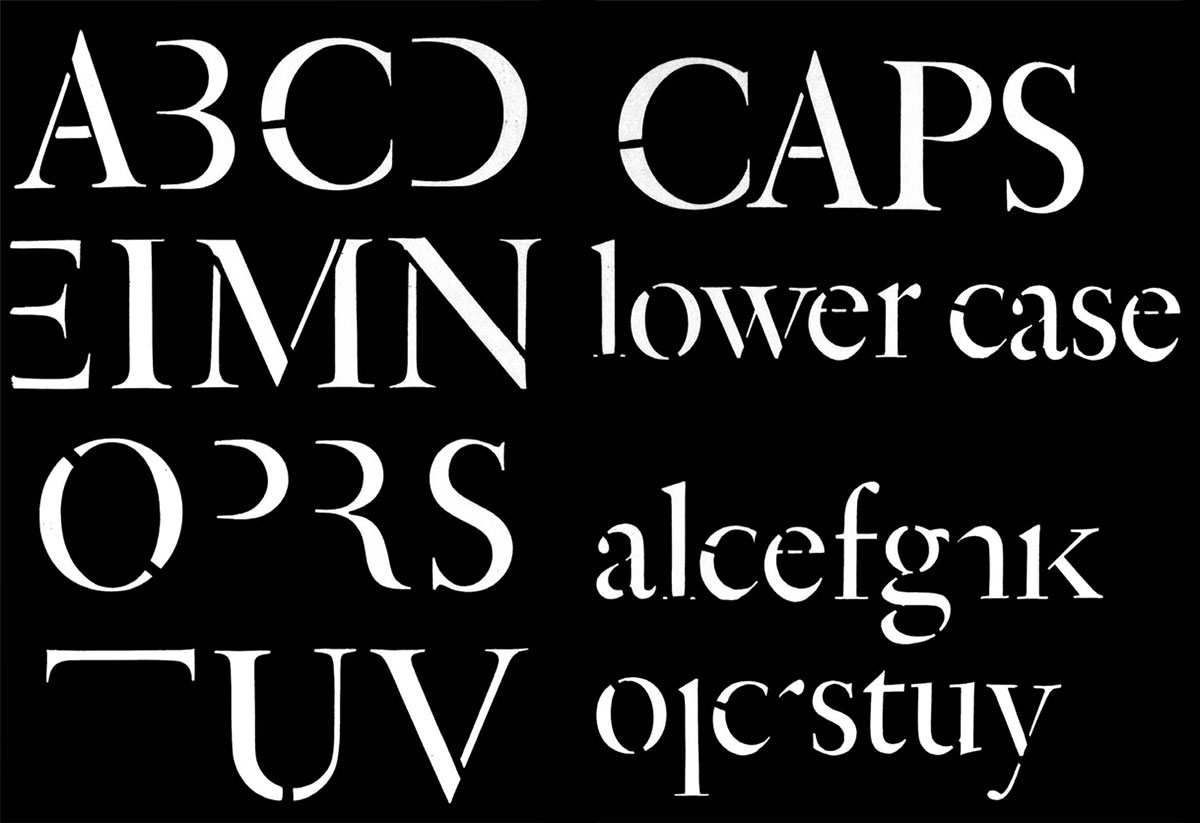
Генотип шрифта
Вера Евстафьева
Без пре­уве­ли­че­ния мож­но ска­зать, что шриф­то­вой ди­зайн как про­цесс чем-то по­хож на ген­ную ин­же­не­рию, на по­стро­е­ние ор­га­низ­ма от мель­чай­шей ча­сти­цы до огром­но­го и слож­но­го це­ло­го. Ми­кро­си­сте­мы вну­три ма­кро­си­стем. Сна­ча­ла вы­стра­и­ва­ет­ся за­ко­но­мер­ность на уров­не об­ще­го сти­ля в од­ном на­чер­та­нии шриф­та, по­том уста­нав­ли­ва­ет­ся связь пря­мо­го и кур­сив­но­го сти­лей, за­тем свя­зи вну­три се­мей­ства. Си­сте­мы и за­ко­но­мер­но­сти встро­ен­ы од­на в дру­гую, как в при­ро­де: от ато­ма до мо­ле­ку­лы, клет­ки, це­ло­го ор­га­низ­ма, ви­да и... до кос­мо­са, на­ко­нец.
Ме­ня по­ра­жа­ет по­доб­ная био­морф­ность шриф­та. Имен­но в этой слож­но­сти при­чи­на то­го, что по­ка не со­здан ге­не­ра­тор но­вых шриф­тов. За­ко­но­мер­но­сти вну­три шриф­тов, их па­ра­диг­ма и ге­но­тип бы­ва­ют прин­ци­пи­аль­но раз­ны­ми, и это уди­ви­тель­но, как и то, что не­воз­мож­но из­ме­рить од­ной и той же ло­ги­кой все шриф­ты. Те шриф­то­вые ди­зай­не­ры, ко­то­рые вы­би­ра­ют путь раз­но­об­ра­зия в сво­ей ра­бо­те (не куль­ти­ва­цию од­но­го сти­ля), зна­ют это ощу­ще­ние воз­ни­ка­ю­щее ещё на эта­пе за­мыс­ла шриф­та: всё на­чи­на­ет­ся как буд­то за­но­во, и с каж­дым но­вым про­ек­том при­хо­дит­ся ис­кать но­вый путь.
Шриф­ты по при­ро­де сво­ей очень раз­лич­ны: мо­дуль­ный шрифт, устро­ен­ный как кон­струк­тор из огра­ни­чен­но­го ко­ли­че­ства ти­по­вых де­та­лей, и, на­при­мер, кур­сив фран­цуз­ской ан­ти­к­вы раз­де­ля­ет про­пасть. Да, ко­неч­но, раз­ные ве­ка — раз­ное мыш­ле­ние, ло­ги­ка, ин­ту­и­ция. Рань­ше один стиль по­сте­пен­но сме­нял дру­гой и прак­ти­че­ски ни­ко­гда не воз­вра­щал­ся сно­ва, вос­при­ни­мал­ся с го­да­ми окон­ча­тель­но уста­рев­шим (ру­сти­ка, ун­ци­ал, го­ти­ка... да­лее раз­ные сти­ли на­бор­ных шриф­тов). И толь­ко мы се­го­дня, в уни­каль­ных ХХ и ХХI ве­ках, «по­сле ис­то­рии», ино­гда име­ем сме­лость хо­дить по­ход­кой раз­ных эпох, пы­та­ем­ся вник­нуть в ло­ги­ку ди­зайн-мыш­ле­ния мно­го­ве­ко­вой дав­но­сти, со­зда­вая ре­кон­струк­ции.
Гер­рит Но­ор­дзей и Эд­вард Ка­тич на­шли вол­шеб­ный ключ к по­ни­ма­нию мно­гих шриф­то­вых форм че­рез ло­ги­ку ин­стру­мен­та. И, на­вер­ное, эти от­кры­тия и ги­по­те­зы при­не­сли боль­шое об­лег­че­ние, ведь они поз­во­ли­ли ска­зать: «Я по­ни­маю, по­че­му имен­но так!» Че­рез па­ру ве­ков по­сле изоб­ре­те­ния на­бор­но­го шриф­та и кни­го­пе­ча­та­ния про «след пе­ра» на­прочь за­бы­ли, фор­мы букв ме­ня­лись до­ста­точ­но от­вле­чен­но, хо­тя и не во­пре­ки ло­ги­ке пе­ра; если смот­реть на рас­пре­де­ле­ние кон­трас­та в бук­вах, то кар­ди­наль­ных из­ме­не­ний не про­изо­шло: че­ре­до­ва­ние тон­ких и жир­ных штри­хов в бук­вах уже сло­жи­лось и остаёт­ся не­из­мен­ным по сей день.
И тем не ме­нее во­про­с «по­че­му так, а не ина­че?» по-преж­не­му име­ет от­вет «так сло­жи­лось». При­чи­ны не­из­вест­ны. Вспо­мню кни­ги Но­ор­дзея и со­гла­шусь: мно­гие объ­яс­не­ния из ис­то­рии шриф­та и пись­ма мож­но при­нять толь­ко с ого­вор­ка­ми, что это пред­по­ло­же­ние, и всё рав­но воз­ни­ка­ет мно­го во­про­сов. В учеб­ни­ках обыч­но встре­ча­ют­ся про­стые объ­яс­не­ния, ско­рее все­го (я на­де­юсь), при­во­ди­мые для луч­ше­го за­по­ми­на­ния фак­тов, но не со­всем убе­ди­тель­ные са­ми по се­бе — сме­на од­них ру­ко­пис­ных по­чер­ков дру­ги­ми обыч­но име­ет до­ста­точ­но слу­чай­ные или субъ­ек­тив­ные при­чи­ны, и ме­нее ве­ро­ят­ны при­чи­ны ра­ци­о­наль­ные (за­бо­та о ём­ко­сти шриф­та, удо­бо­чи­та­е­мо­сти и дру­гих па­ра­мет­рах — за­да­чи бо­лее по­зд­ние).
По­че­му для гре­че­ских и ки­рил­ли­че­ских пис­цов на­пи­са­ние букв уста­ва опре­де­лён­ным уста­нов­лен­ным об­ра­зом бы­ло важ­нее бо­лее удоб­но­го оди­на­ко­во­го на­кло­на пе­ра при пись­ме? И от­ку­да у них бы­ла уве­рен­ность, что не­ко­то­рые бук­вы долж­ны быть уз­ки­ми, на­пи­сан­ны­ми в иной ло­ги­ке, чем дру­гие зна­ки?
Шриф­то­вая эво­лю­ция очень по­хо­жа на эво­лю­цию в при­ро­де: мож­но пред­по­ло­жить при­чи­ну по­яв­ле­ния тех или иных форм, гра­фем, пред­по­чте­ний в об­ла­сти про­пор­ций, но ред­ко мож­но уста­но­вить эту при­чи­ну без­ого­во­роч­но. Хо­тя пись­мен­ность и шрифт — ре­зуль­тат че­ло­ве­че­ской де­я­тель­но­сти, раз­ви­ва­ют­ся они так же не­пред­ска­зу­е­мо и са­мо­сто­я­тель­но, как и при­ро­да.
Ве­ро­ят­но, сбои (как ошиб­ки сти­ля, так и не­ожи­дан­ные му­та­ции за­ко­но­мер­но­стей) воз­ни­ка­ют в шриф­тах с ча­сто­той не мень­шей, что и му­та­ции у жи­вых ор­га­низ­мов.
В Гель­ве­ти­ке нож­ка бук­вы R с из­ги­бом и ма­лень­кой ступ­нёй на
ней не вы­зы­ва­ет у нас во­про­сов — «так на­до», хо­тя, учи­ты­вая од­но­род­но­сть, оди­на­ко­вую про­стую фор­му, про­хо­дя­щую че­рез весь ал­фа­вит в этом шриф­те, кто-то на­ри­со­вал бы иной, бо­лее ла­ко­нич­ный из­гиб. Ду­маю, в на­ча­ле XXI ве­ка R у боль­шин­ства ди­зай­не­ров по­лу­чи­лась бы со­всем дру­гая! На­вер­ное, есть ло­ги­ка вре­ме­ни, по­ко­ле­ния, и она силь­нее, чем ло­ги­ка од­но­го ав­то­ра. И в ка­кой-то мо­мент мы со­гла­си­лись, что без этой де­та­ли стиль су­ще­ство­вать не мо­жет.
Ино­гда ис­клю­че­ния пре­крас­ны, и да­же стран­но, что они не бы­ли под­хва­че­ны и не ста­ли нор­мой. Взгля­ни­те, на­при­мер, на про­пис­ную бук­ву U ни­же, так мяг­ко и де­ли­кат­но впи­сан­ную в ритм осталь­ных про­пис­ных, близ­кую и пря­мым, и округ­лым бук­вам и од­но­вре­мен­но не­су­щую па­мять о своём пред­ке, бук­ве V. Она, к сло­ву, от­ве­ча­ет на во­прос, по­че­му так рас­пре­де­лён кон­траст в бук­ве U. Но по­че­му-то та­кая фор­ма бук­вы не бы­ла от­ме­че­на вни­ма­ни­ем и не ста­ла рас­про­странён­ной. За­гад­ка...
Salmasius: Pliny. Utrecht, 1689. Victoria and Albert Museum, London•J. Sutton, A. Bartram, An Atlas of Typeforms (Lund Humpfries, London, 1968).
Эту фор­му вспо­мнят (или за­но­во при­ду­ма­ют) во вто­рой по­ло­ви­не ХХ ве­ка, она по­явит­ся в ди­на­мич­ных ал­фа­ви­тах То­ма Пёр­кин­са, в ря­ду букв, об­ла­да­ю­щих уди­ви­тель­но изящ­ной пла­сти­кой.
Том Пёр­кинс (Tom Perkins). Incised and painted Welsh slate 48×19 cm, 1988.
Ду­маю, шрифт, бу­ду­чи стро­и­тель­ным ма­те­ри­а­лом в ти­по­гра­фи­ке, дол­жен быть од­но­знач­ным в сво­ём об­ра­зе, креп­ким и цель­ным. Так, в стро­и­тель­стве кир­пич дол­жен быть ка­че­ствен­но обо­жжён и не дол­жен кро­шить­ся, це­мент важ­но пра­виль­но за­ме­шать, а брус — про­су­шить. Эк­лек­ти­ка раз­ру­ша­ет шрифт. Пусть ти­по­гра­фи­ка сти­ли­сти­че­ски ва­рьи­ру­ет­ся в раз­ные го­ды и де­ся­ти­ле­тия, но шрифт дол­жен быть мак­си­маль­но по­сле­до­ва­те­лен и ве­рен вну­трен­ней ло­ги­ке.